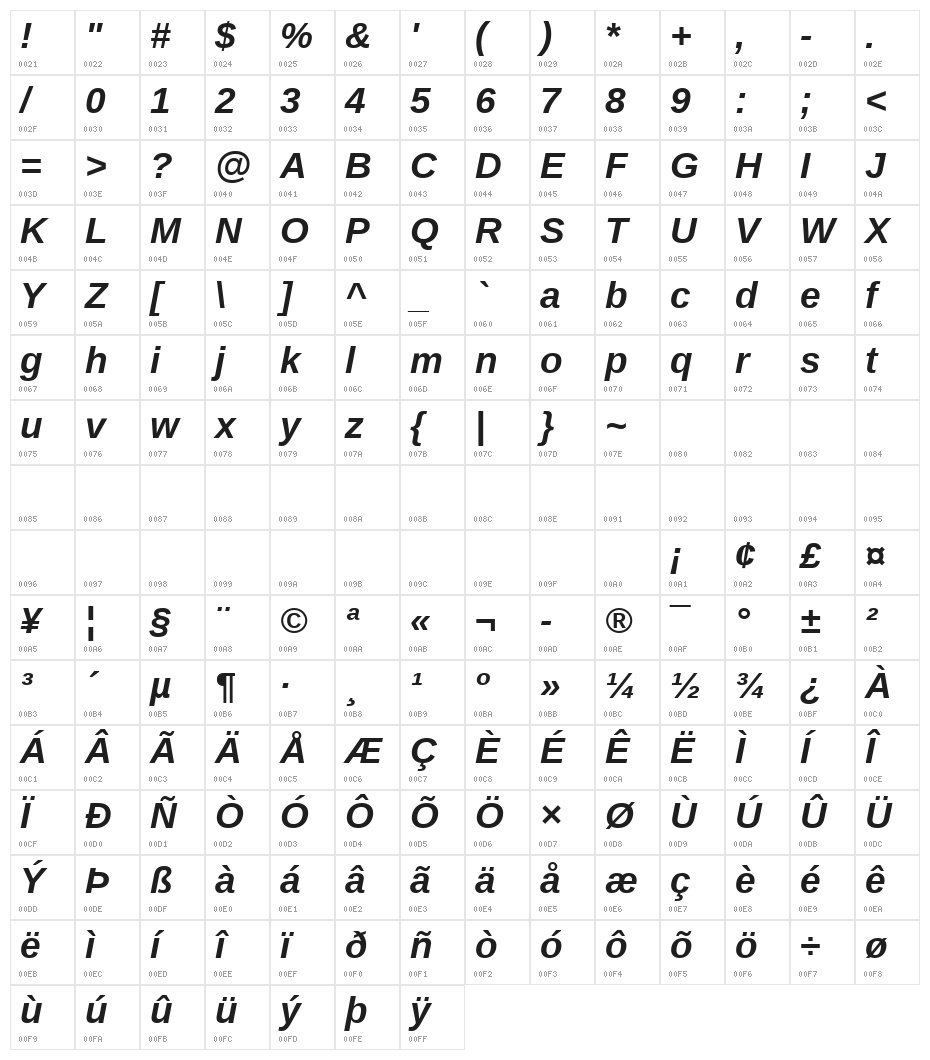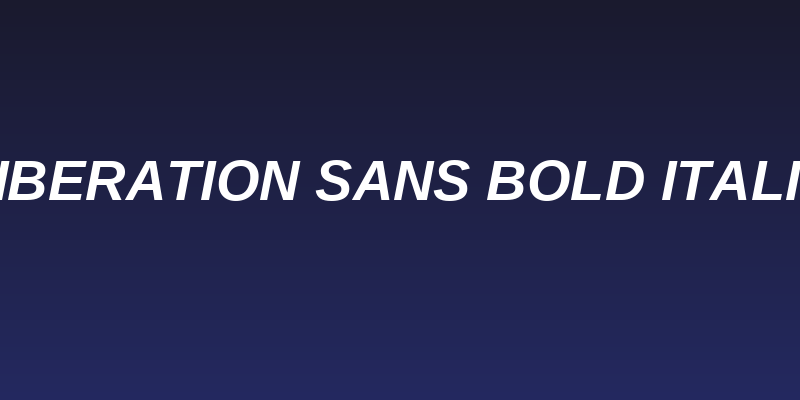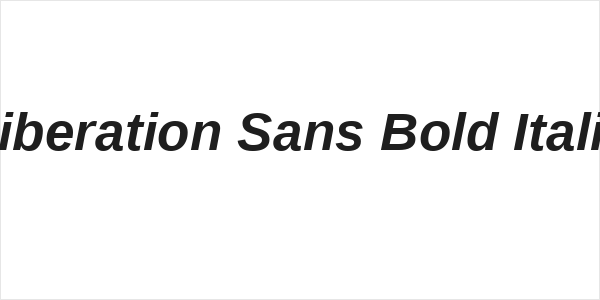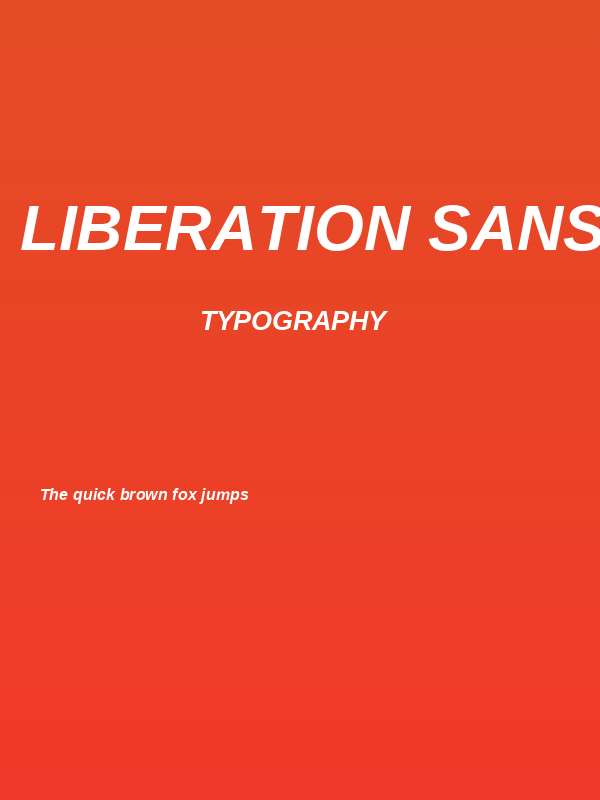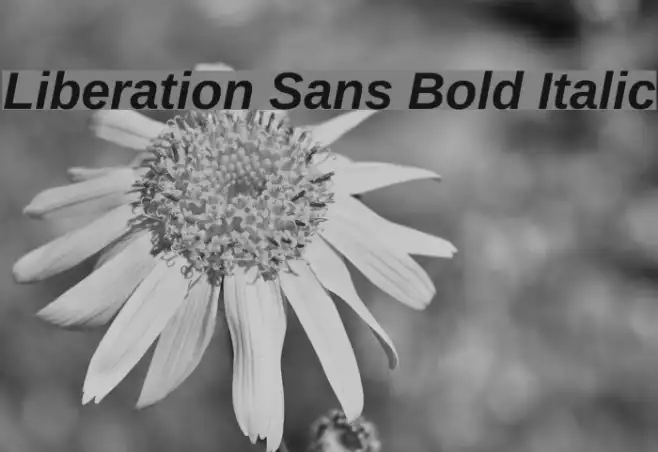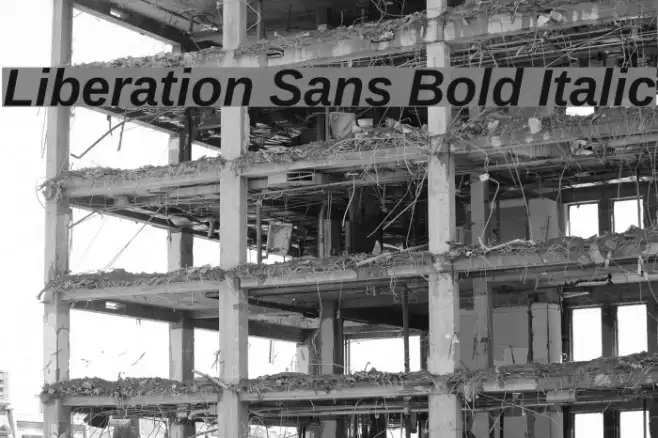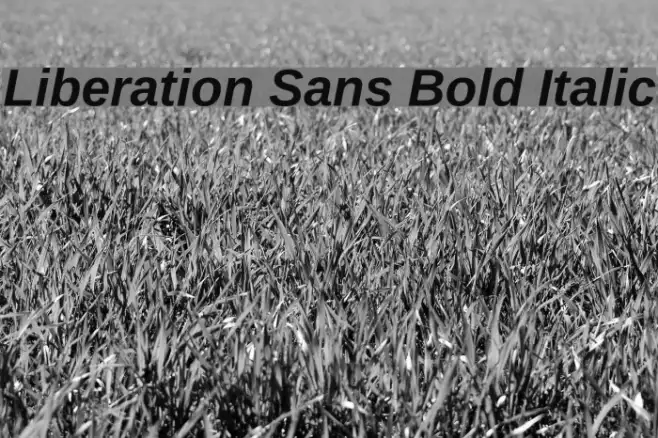
Liberation Sans Bold Italic Font
| Cas d'utilisation | Headlines, Logos, Advertising |
| Projets proposés | Ideal for branding, advertising, headlines, and digital content where a strong, modern presence is required. |